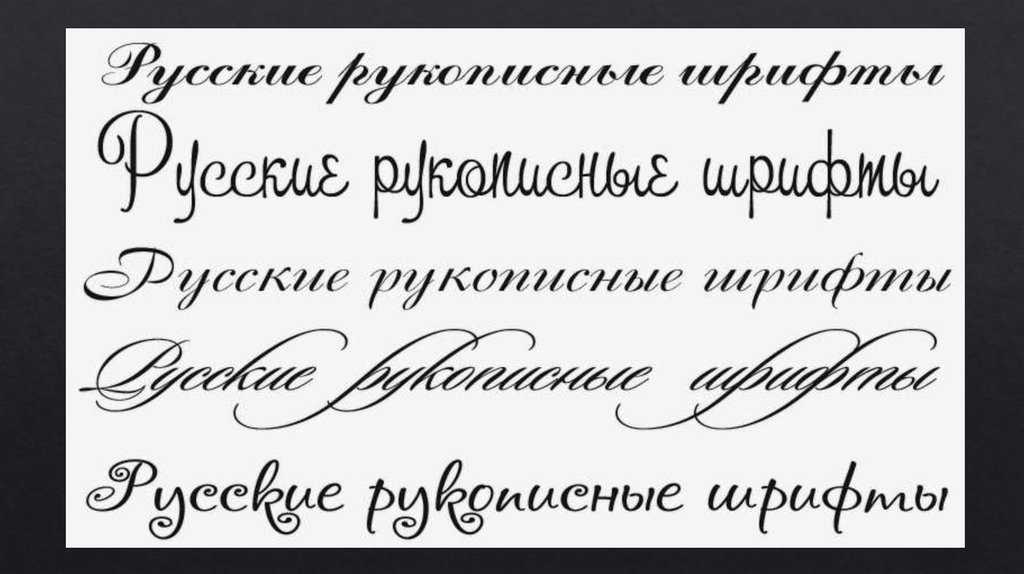
Красивые рукописные шрифты кириллица: Рукописные шрифты — русские скачать бесплатно
Рукописные шрифты: подборка и ресурсы
Рукописный шрифт – это разновидность шрифтов, которые создают специальной ручкой или пером. Каллиграфический текст смотрится очень красиво, будто был написан вручную.
Если вы в поиске красивого рукописного шрифта для бренда, то следует отдать предпочтение платным и профессиональным вариантам. В процессе выбора следует обратить внимание на то, какое количество начертаний входит в набор.
Чем больше версий разработал автор, тем лучше. Варианты с тонкими начертаниями станут идеальными для печатного издания, а варианты с полужирными – для вывески или заголовка. Это сэкономит время на поиск дополнительного шрифта.
Чтобы разработать уникальный фирменный знак, не нужно искать или покупать готовую версию каллиграфического шрифта. Для этой работы может быть привлечен профессиональный каллиграф или летерер, то есть художник, задачей которого станет создание короткой надписи для определенной компании.
Важно: в процессе выбора рукописного шрифта необходимо обратить внимание, какой язык был использован при его создании. Варианты, написанные на латинице, не подойдут для написания кириллических текстов.
Из-за набирающих актуальность трендов на красивые рукописные заголовки, логотипы и подписи, все больше и больше модных блогеров в Инстаграм прибегают к услугам художников.
Инфлюенсеры используют уникальные шрифтовые сочетания, чтобы оформить вечные сторис, аватарки и собственные веб-сайты.
У рукописных шрифтов есть серьезный минус – людям может быть сложно воспринимать их визуально.
Поэтому их обычно не используют для написания больших текстов. Этот недостаток следует учитывать в процессе выбора красивого каллиграфического шрифта.
10 Бесплатных рукописных шрифтов для вашего дизайна
Рукописные шрифты или курсивные, очень популярны в сети, поскольку они часто используются в рекламных заголовках или типографике. Но когда дело доходит до огромного изобилия бесплатных ресурсов в сети – особенно бесплатных шрифтов, бывает сложно найти среди множество одинаковых или некачественных шрифтов тот который нужен. Вот именно для этого, мы сделали эту подборку качественных и бесплатных шрифтов.
Если у вас есть нарисованный на бумаге шрифт, то с небольшим знанием того, как отсканировать документ в иллюстрацию и загрузить в программу генерирующую шрифт, вы просто можете создать Ваши собственные рукописные шрифты.
01. The Woodlands
Начало десятки бесплатных рукописных шрифтов с красивым дизайном, представляет шрифт, woodlands, созданный проектировщиком Джереми Весси. Woodland был создан, чтобы дать дизайнерам свободную альтернативу, которая поможет, в создании красивого дизайна. Woodland бесплатен и для личного и для коммерческого использования.
02. Milkshake
Типограф Лора Уортингтон создатель этого шрифта который называется Milkshake. Комментарий автора: «Я намеревался создавать дизайн, который будет приятным, читаемым и универсальным.»
03. Variane Script
Создатель этого шрифта Boy Moch Tomi. Этот рукописный шрифт возвращается к старым добрым временам классического дизайна. Современный взгляд на классическую пропись, напоминает о начале американского рекламного движения 20-го века и может опереденно дать Вашему бренду всплеск винтажного очарования.
04. Fabfelt Script
Французский графический дизайнер Fabien Despinoy — и его бесплатный рукописный шрифт Fabfelt. «Я пытался разработать рукописный шрифт без зернистости, который будет похож на ретро», комментирует автор.